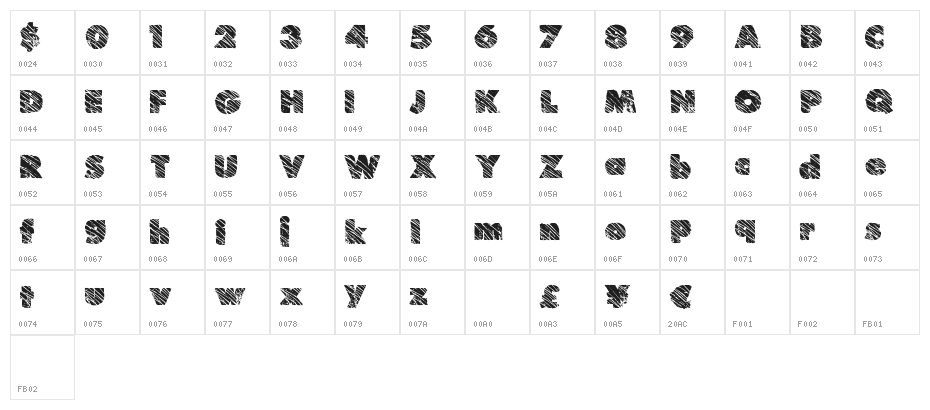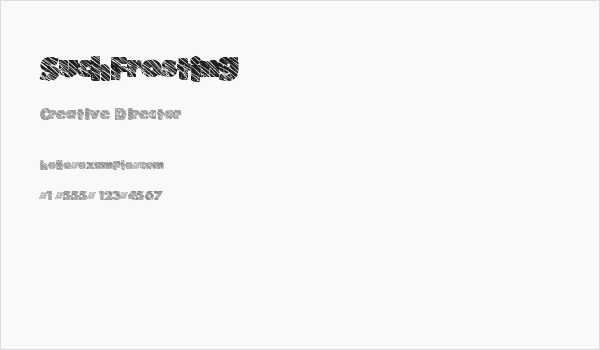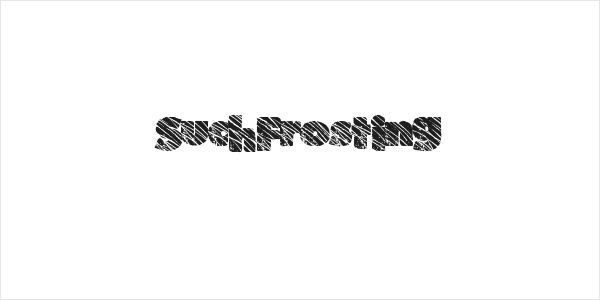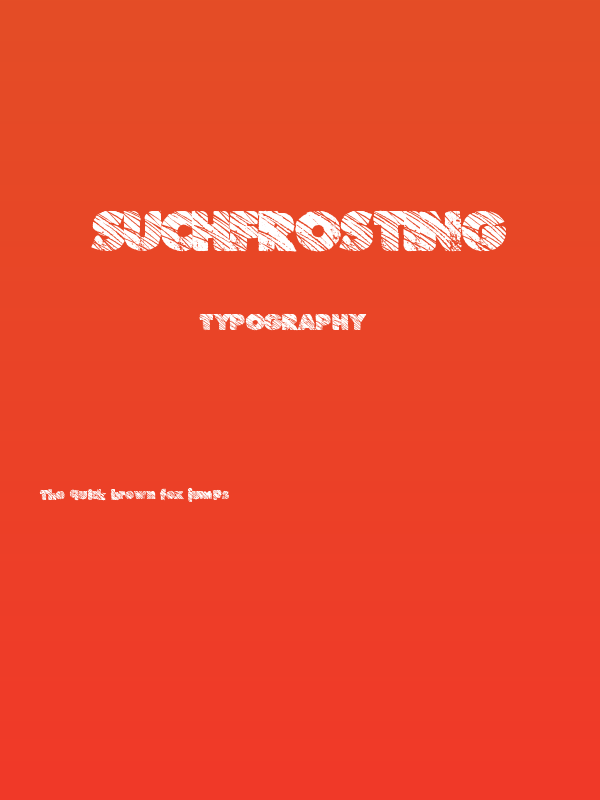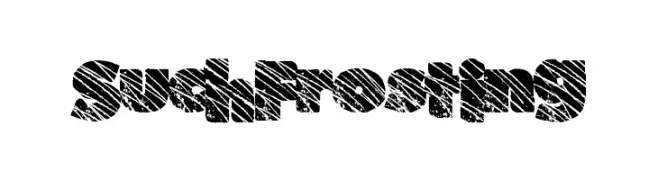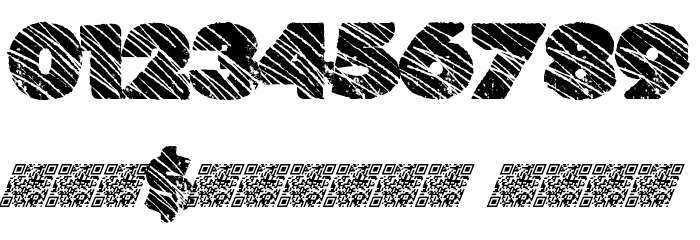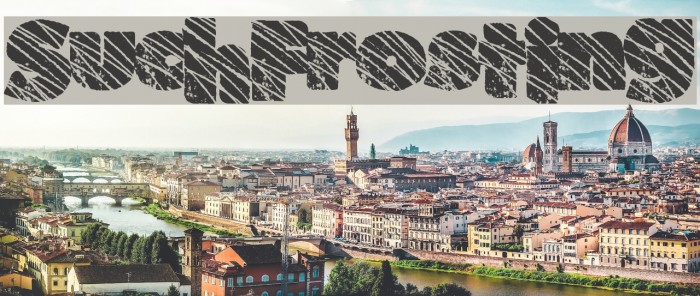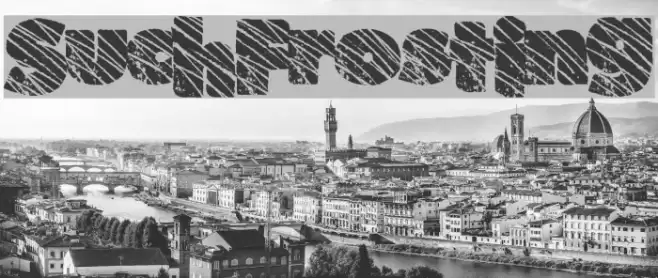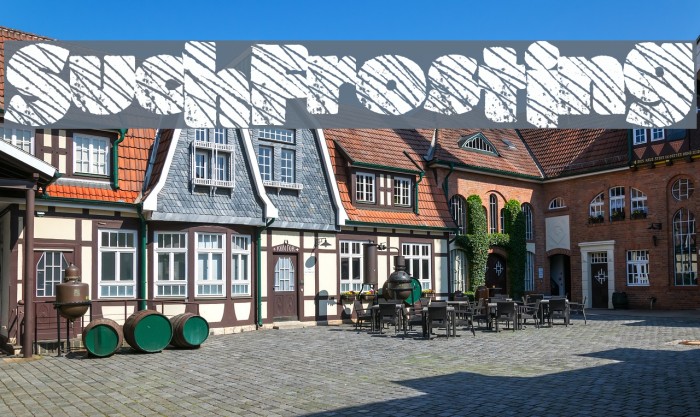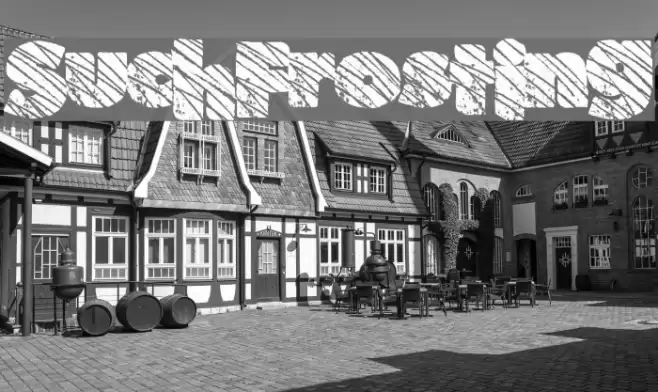
SuchFrosting Font
✎ Distorted Eroded
| النمط العام | Vintage |
| مشاريع مقترحة | Ideal for posters, album covers, branding for edgy or industrial-themed products, and any design needing a rugged, vintage touch. |